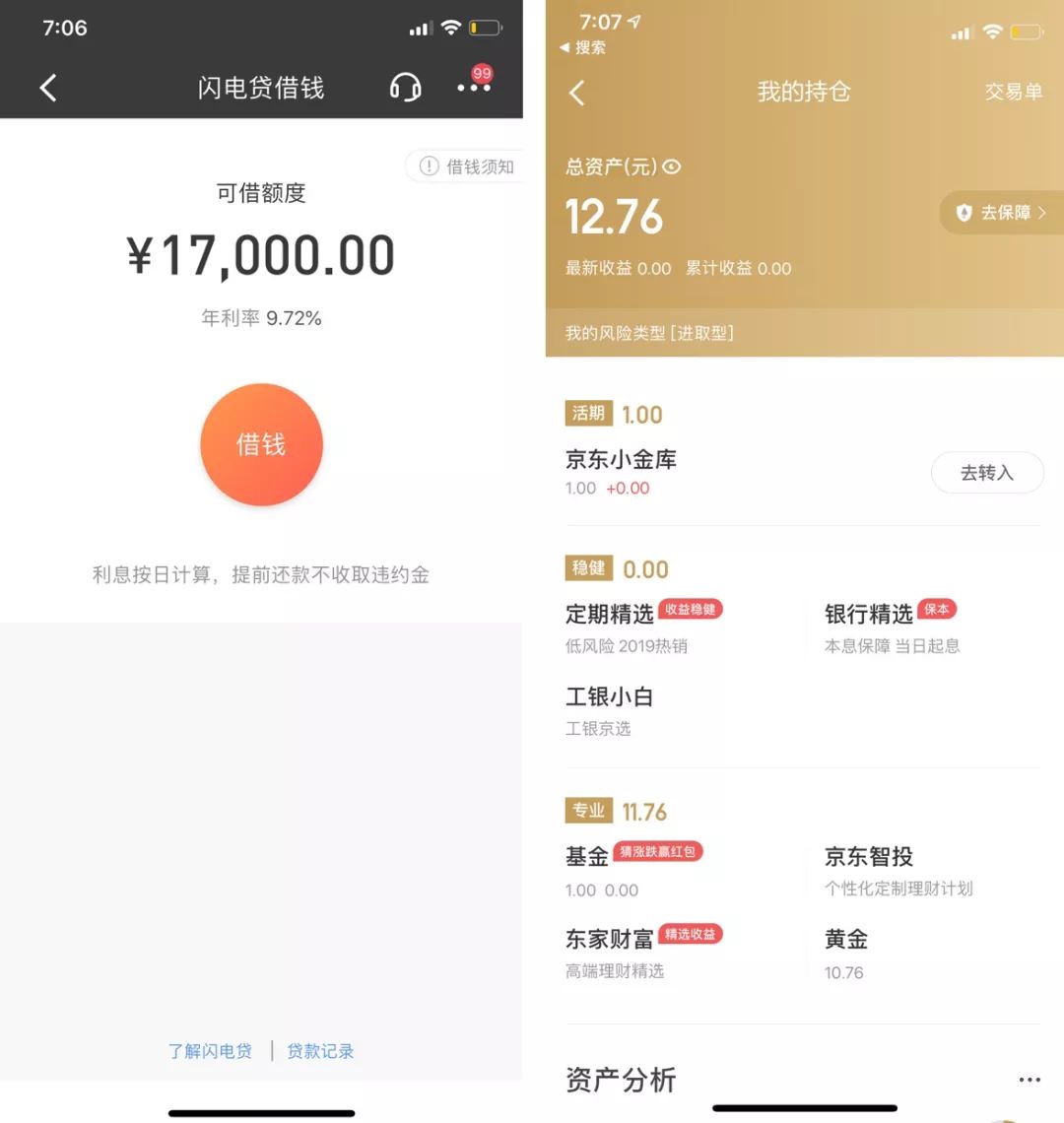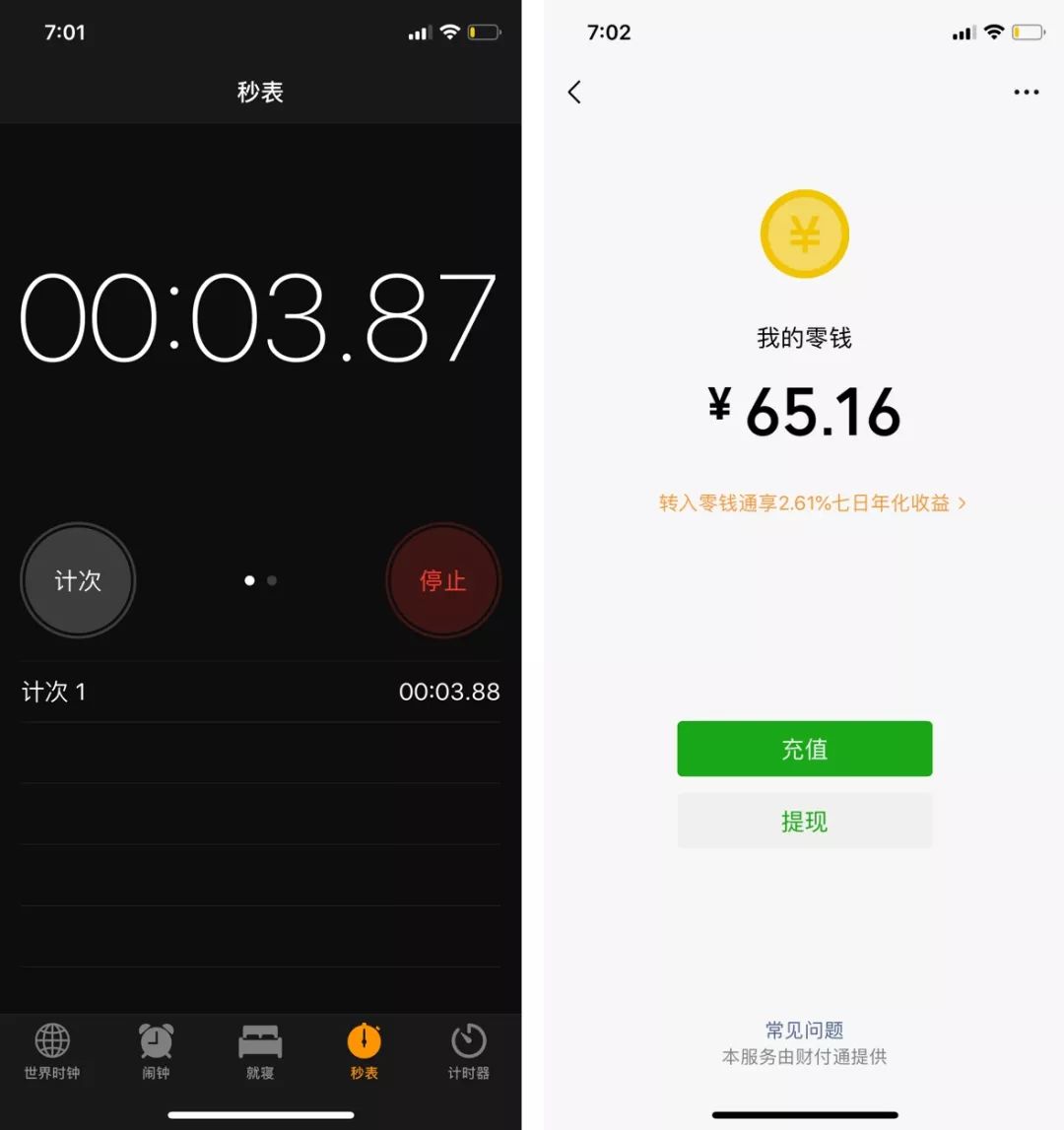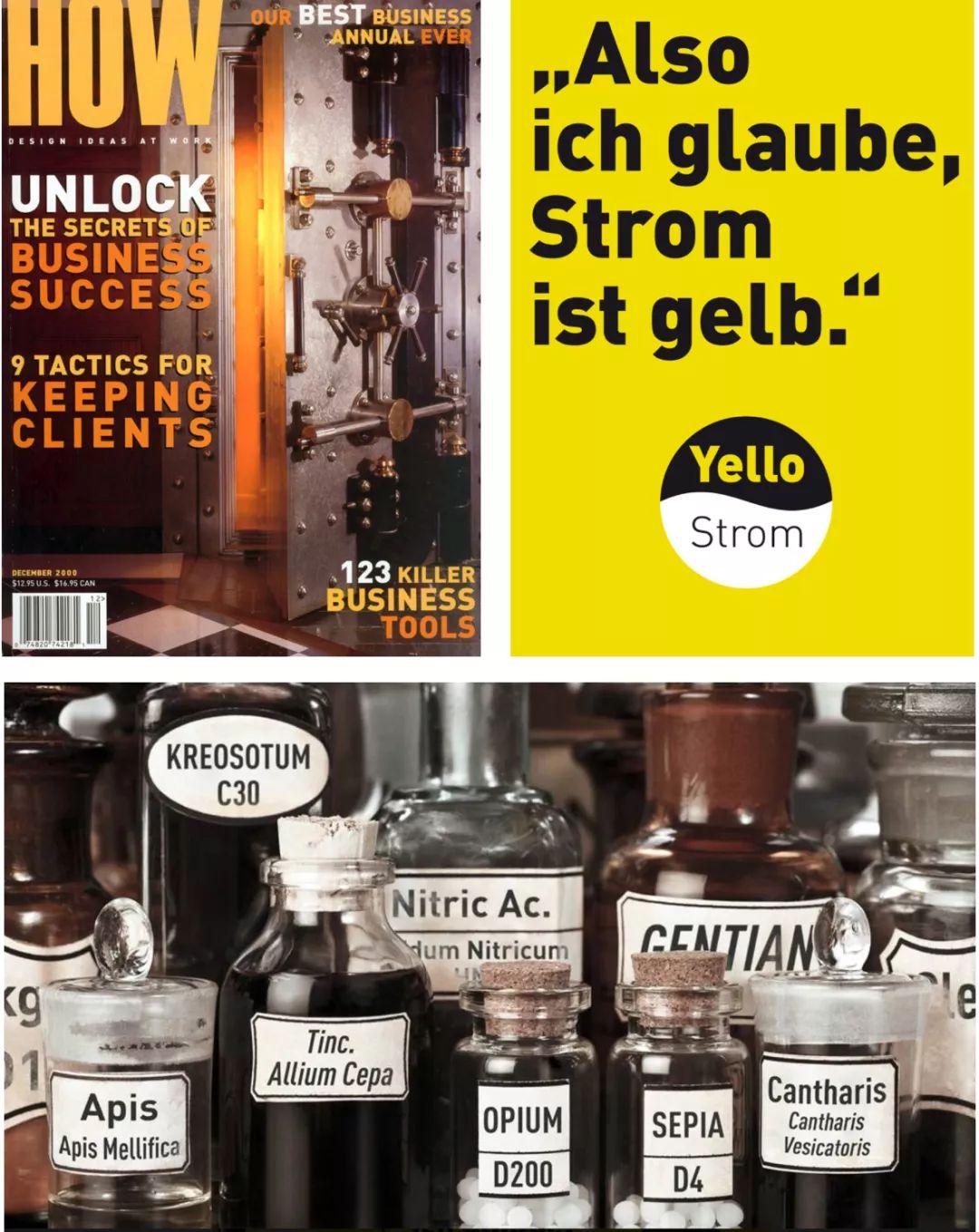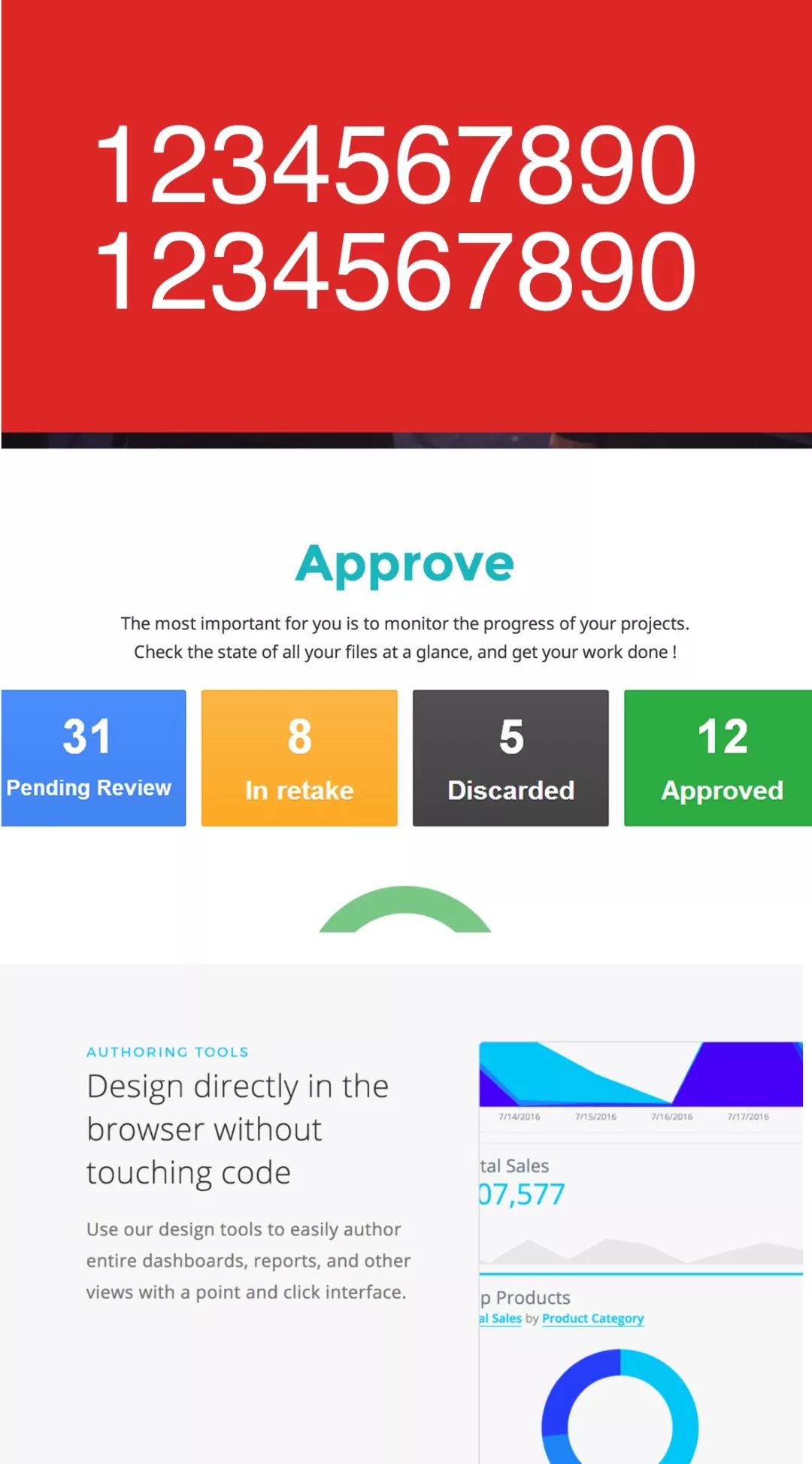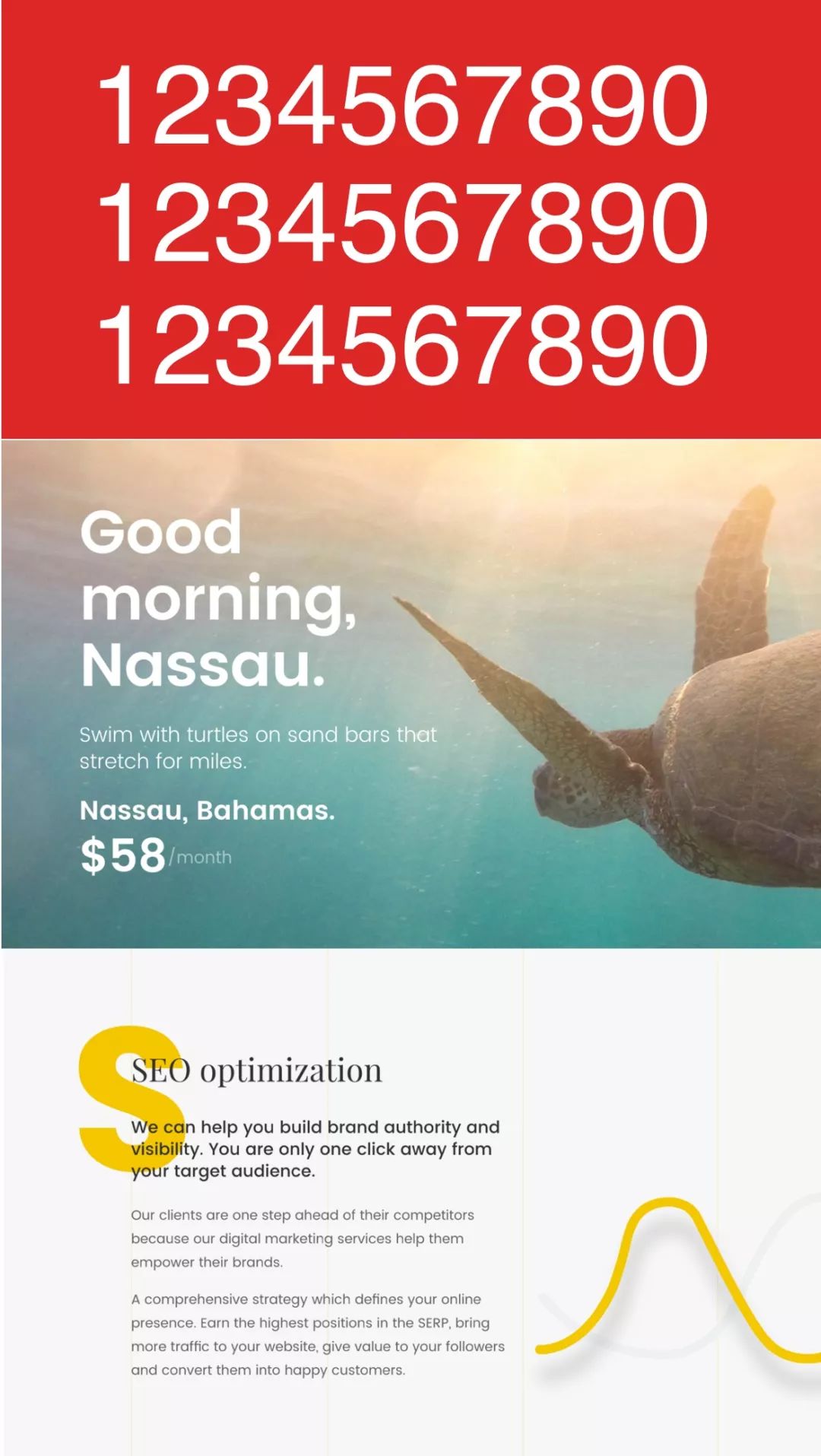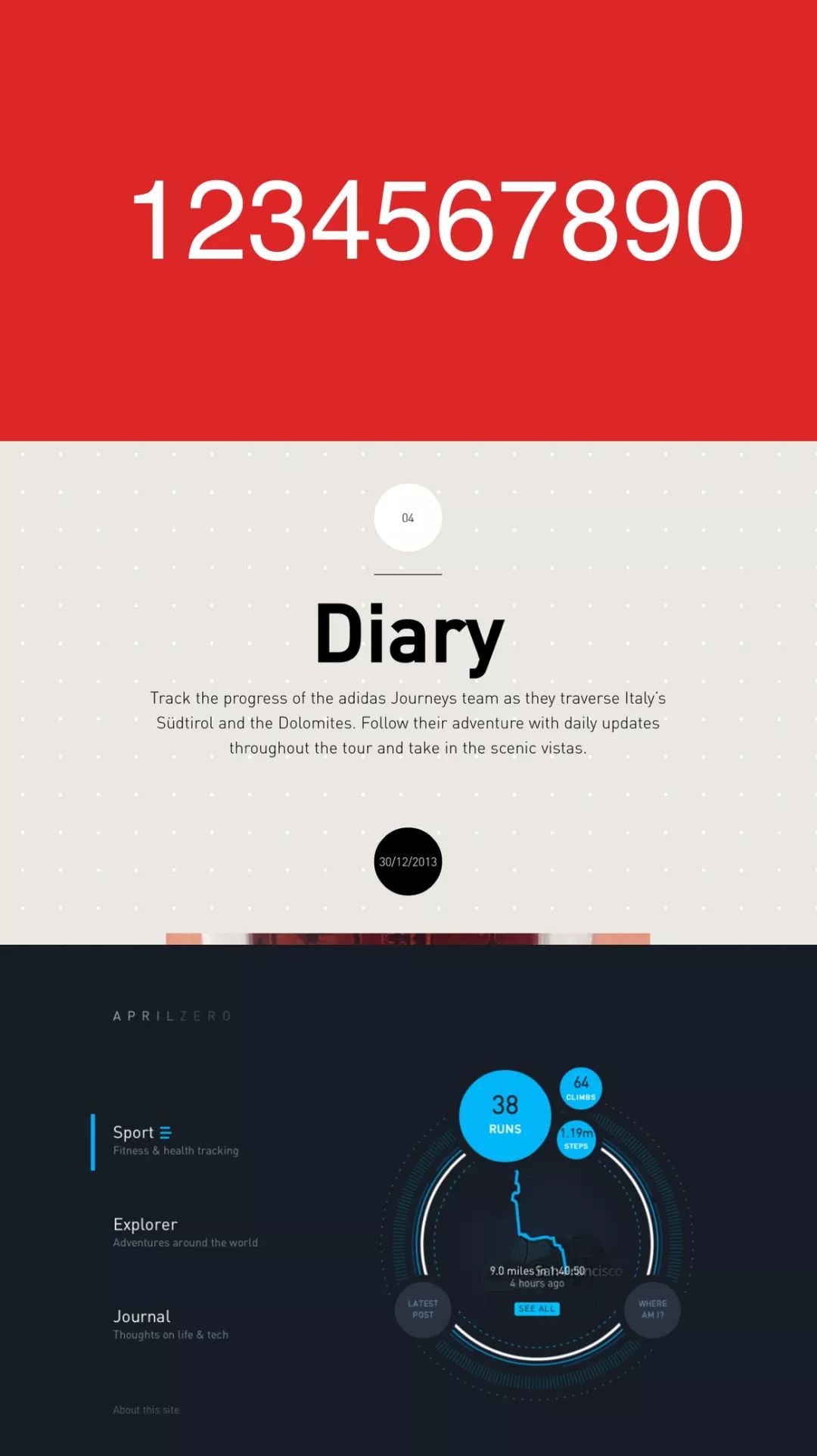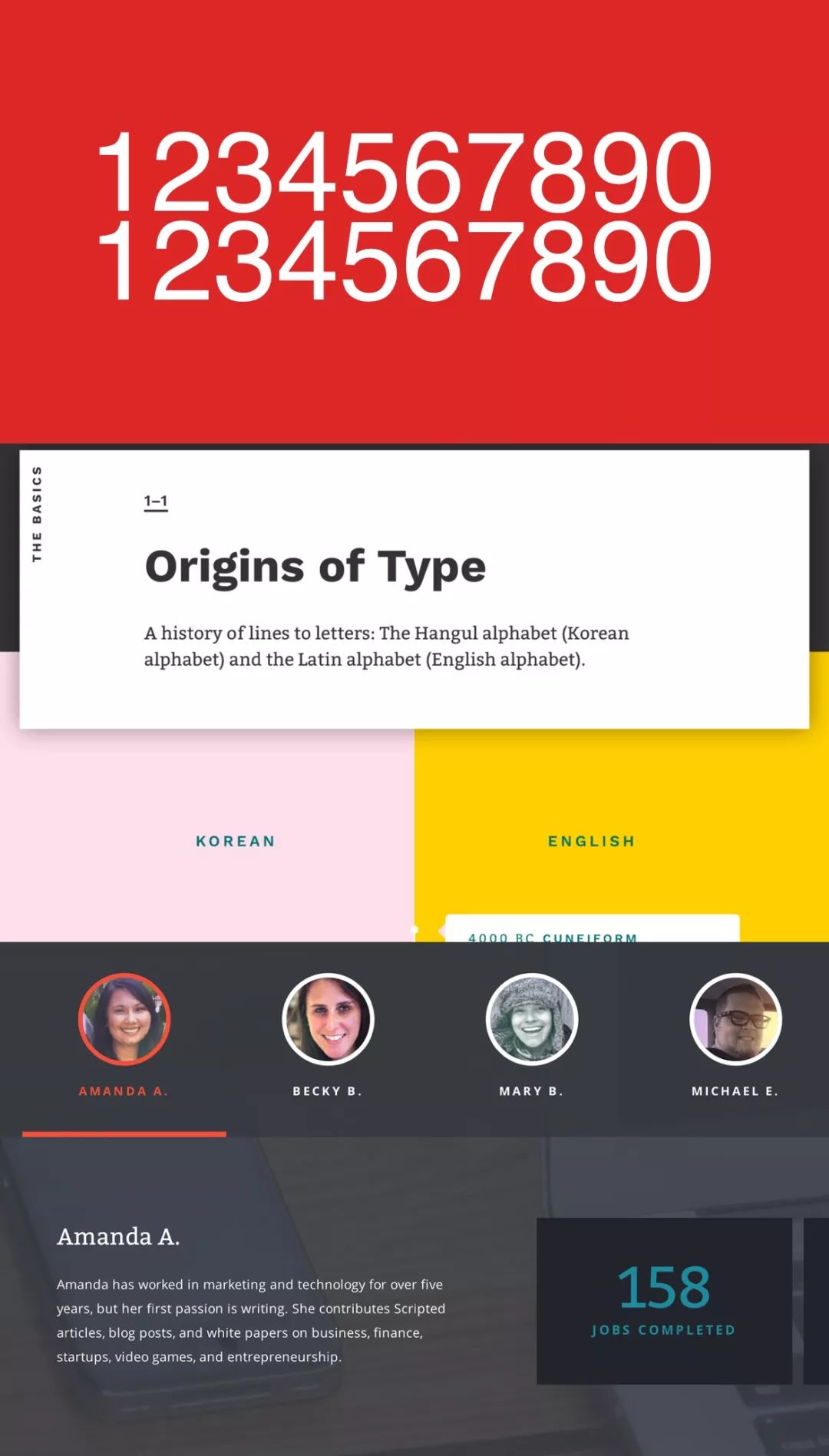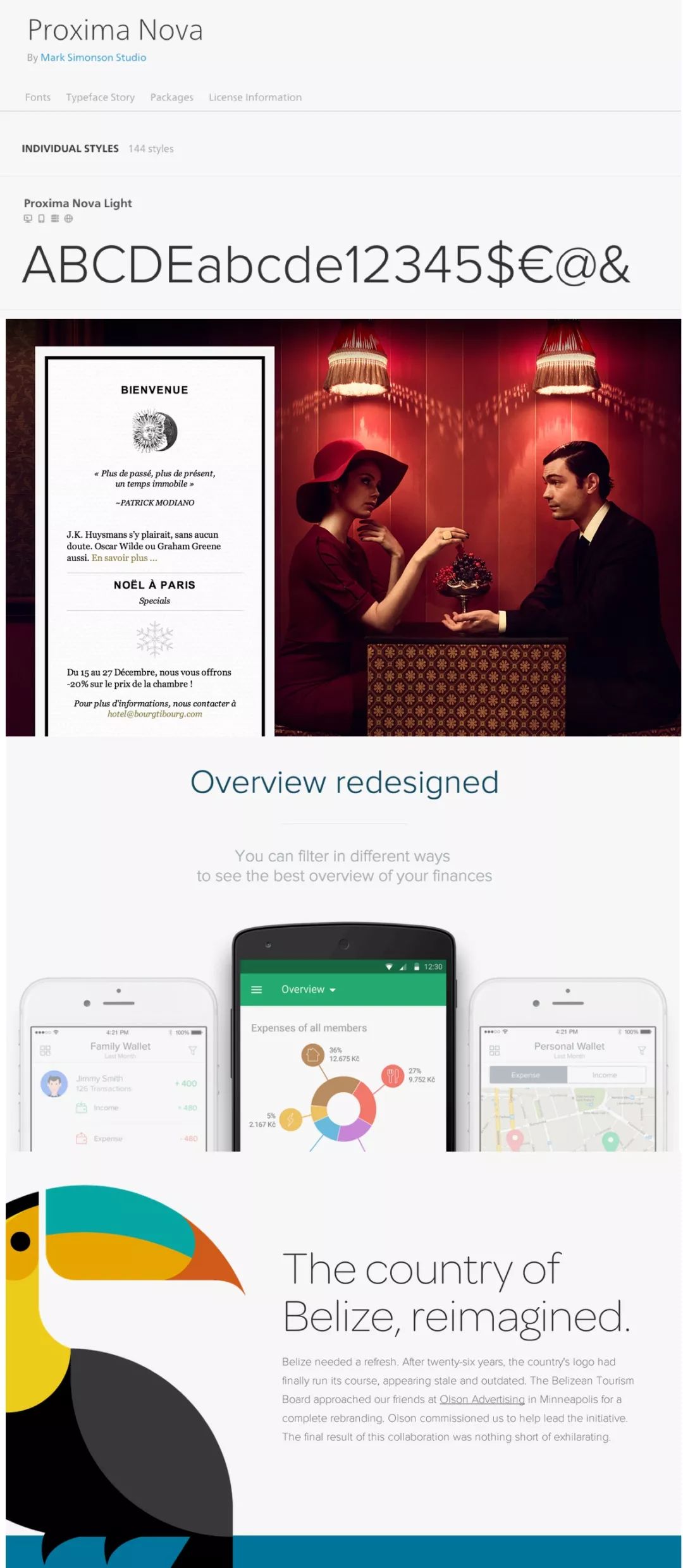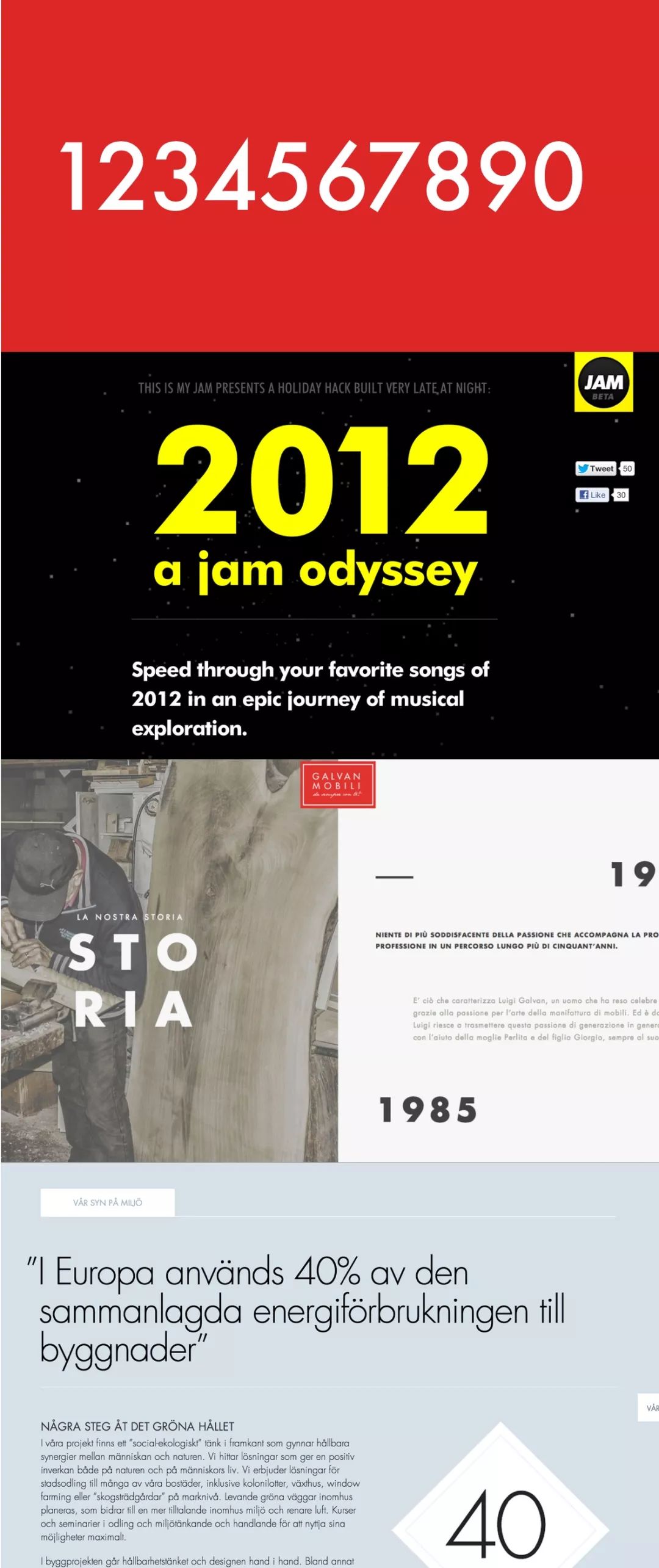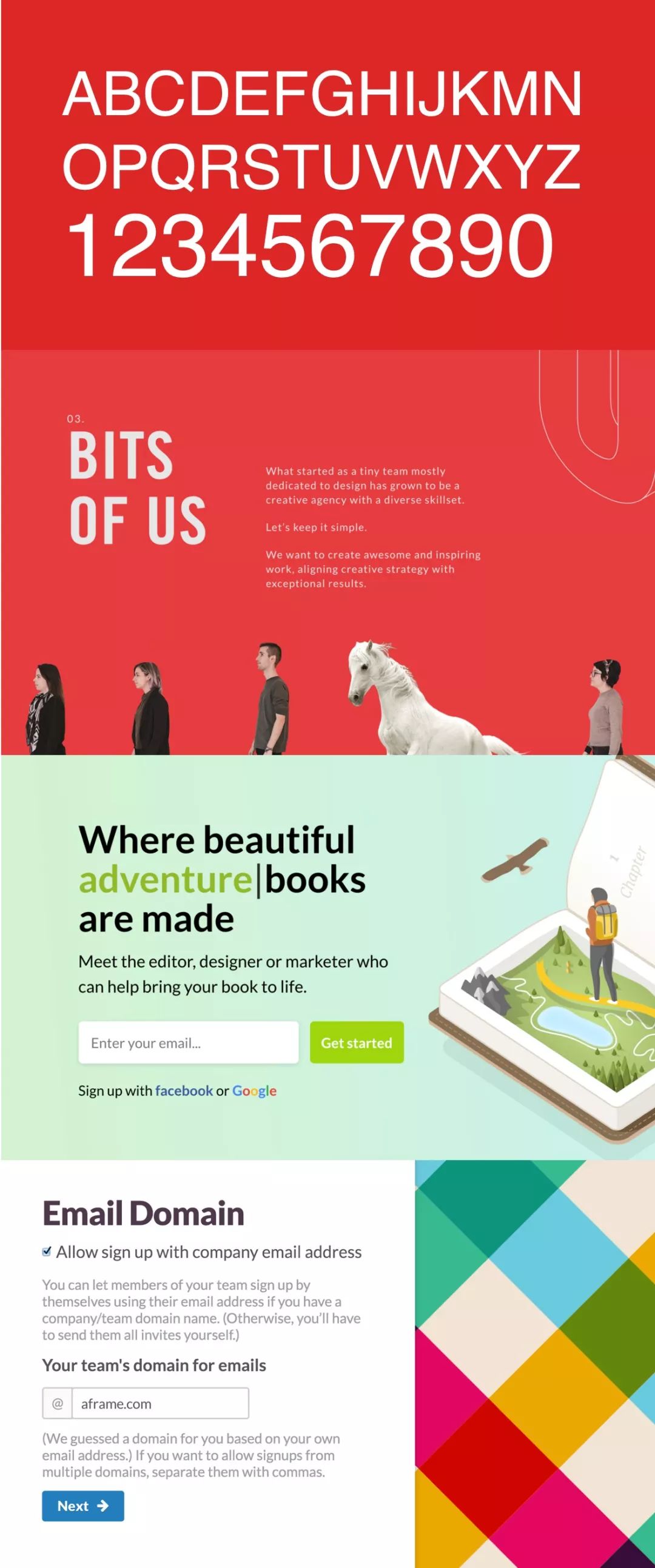
如何让设计中的数字也好看
背景
上周我们一起聊了,界面常用的中文字体和英文字体,本期聊聊数字字体,数字在设计中其实占比还是很大,特别是在金融和电商设计中,数字字体,一直是情感的传递,设计细节的体现!那么今天和大家分享下在电商设计和金融设计中,常用的数字字体有哪些!
字体的骨架
结构部分
分享前我们先要了解下字体结构:
顶部:字体中最高字形的基线上方的最大距离
上升:单个字母的基线上方的建议距
下降:单个字母的建议距离低于基线
底部 :  字母中最低字形的基线以下的最大距离
行距:指代字体连行的基线间的距离
基本的英文字体都是由这些单位组成的,所以在了解这些基础后,才更加方便我们设计中如何选择字体。
身体部分
前面那张图是字体的上下结构关系,那么这张图更多是字体本身由那些元素组成:
躯干:也就是数字本身的横竖,比较笔直的笔画
字碗:顾名思议,带弧形的笔划
字环:字体被包裹的空间
字距部分
在字距上,业内两种做法,一种是每个字体相同的大小,比如我们熟悉的lato,也有一种做法是根据每个字母本身一个大小,比如1会小一些,9会大一些,这两种布局方式有好有坏,我个人更推荐前者,每个字母间距采用一样的!
需要注意的点
▲ 通常我们很多时候,网上去免费找一些数字字体,或者选择几款热门字体时候,一定需要注意检查“$”和“%”“¥”符号。
▲ 另外在选择字体时候,一定需要仔细检查每个字符,比如数字中最容易混淆的就是1和7,0和O。
常用数字字体
那么我们做金融设计或者电商设计,数字字体到底用哪几个呢?在选择之前,先来看看互联网公司都在使用哪些字体。
▲ 苹果系统:使用的旧金山字体SanFrancisco,微信:DIN的字体基础上微调
▲ 招商银行:DIN字体;京东金融:DIN的字体,重新进行了设计
▲ 百度金融:DIN字体基础上调整6.9,支付宝:苹果原生Helvetica Neue
▲ 富途:苹果原生Helvetica Neue,韩国SSG:苹果原生Helvetica Neue
所以通过以上简单调研,我们不难发现,现在国内外大多数金融产品数字字体都是运用苹果自带数字字体,以及Din这个字体基础上调整,那么为什么Din这个字体这么受设计师喜爱呢?
Din故事
DIN 是德国标准协会,Deutsches Institut für Normung 的首字母缩写。1975年起,德国政府把DIN作为国家标准体系,DIN 标准在国际和欧洲范围内被广泛使用。DIN 字体继承了严谨可识别度高,被广泛运用。
▲ 在德国公路指示牌,以及机场,地图里面,大多数运用Din字体作为引导字体。
▲ 在很多杂志包装中,也可见大量Din字体的运用,德国人的严谨在这个字体中体现的淋漓极致。
▲ 缺陷:前面我们说了DIN在公路以及杂志,平面设计中用的很多,但是直接拿到互联网APP设计中各种复杂的场景,DIN就没有那么的完美,如图中,4的开头较大,以及5,6字体的圆形不够一致,7缩小后识别度问题,所以很多公司都会基于这些问题进行二次设计,这也是前面竞品分析里面提到,为什么微信,京东,百度会这个基础上再设计的原因。
常用数字字体
如果只推荐一个数字字体,我肯定会推荐Din,但是Din并不免费,价格不便宜,如果需要运用每年会有一笔不小的费用,所以如果公司不愿意购买,你可以Din基础再重新设计一版本,也可以使用一些其他不错的数字字体,接下来给大家推荐一些免费版权使用的!
1.Gaoel
如果都是用Din其实也容易看腻歪,首先推荐的这个我特别喜欢,整体字体设计很圆润,年轻化,可爱非常适合一些偏年轻化的产品,同时字重非常适合金融产品的字重效果!
▲ 在支付宝备用金页面中,就运用了类似这种比较圆润有活泼感数字字体!大家可以尝试下这个字体在你界面中效果,保证不会失望。
2.Montserrat
谷歌免费字体中很优雅的一个字体,用在数字上或者界面中都非常的优雅。
3.Poppins
谷歌免费字体中经常被用到的一个字体,除了9稍微显得有点笨拙以外其他都挺现代的。
4.Bitter
谷歌旗下的同样广泛运用到各种设计中,字体和英文字体都很好用。
5.Fjalla One
Din字体的替代品,很多人一直在寻找的,如果公司不愿意购买Din字体,那么谷歌旗下这个字体非常完美的替代品,使用出来的效果和Din也不会相差很多。
6.Graduate
谷歌旗下免费的,非常英伦风格和学院风的一款数字字体,用在海报或者一些个人化活动页面效果非常好,当然作为英文排版也是很高级。
7.Futura
谷歌旗下免费的,这个字体无论英文还是数字都非常现代化,非常干净利索的一款字体,做到PPT里面效果非常好。
8.Proxima Nova
这款不免费,当然收费也非常对得起他这个价格,效果大家可以自己看,非常优雅,现代。
9.Gotham
非常适合发布会,极简的网站设计,或者海报,非常现代干净的一款字体,效果如图,dribbble上各种好看的设计里面都跑不了这款字体。
10.Lato
非常现代科技感的一款字体,无数知名app在用的字体,同样出自谷歌旗下,保证你不会出错的一款字体,之前天猫用过,效果非常好。
衬线字体
Playfair Display
如果只让我推荐一款衬线英文字体,那么必须是Playfair Display莫属,心头大爱的字体,古典,现代优雅于一体,不知道多少大牌一直用这个字体做设计。
如果你一直在寻找一款衬线英文字体,那么这个必须首先,效果直接看图!